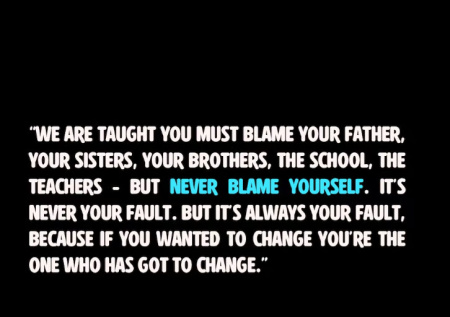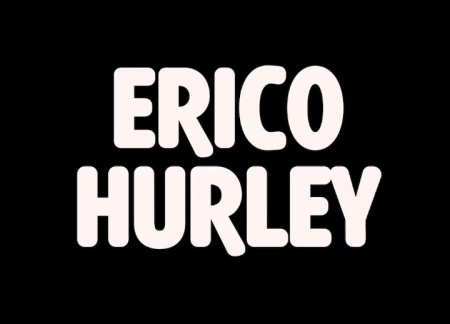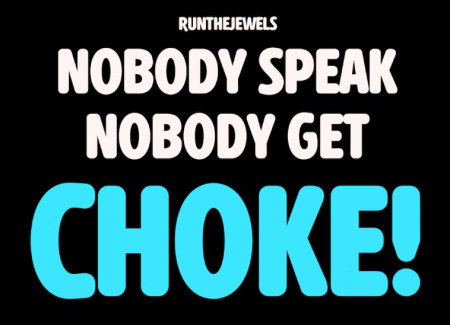
فونت انگلیسی نرم Rydero
Rydero یکی از نرم‌ترین کاراکتر sans serif است که تا به حال وجود داشته است . فونت انگلیسی نرم Rydero از بیش از 100 زبان چند زبانه پشتیبانی می کند. این فونت برای طراحی لوگو، رسانه های اجتماعی، عنوان فیلم، عنوان کتاب، یک متن کوتاه حتی یک حرف متن طولانی مناسب است. با فونت Rydero یک کار خیره کننده بسازید. با تهیه اشتراک ویژه از سایت gfx این فونت را دانلود کنید و طراحی های خود را حرفه ای تر از قبل ارائه دهید.